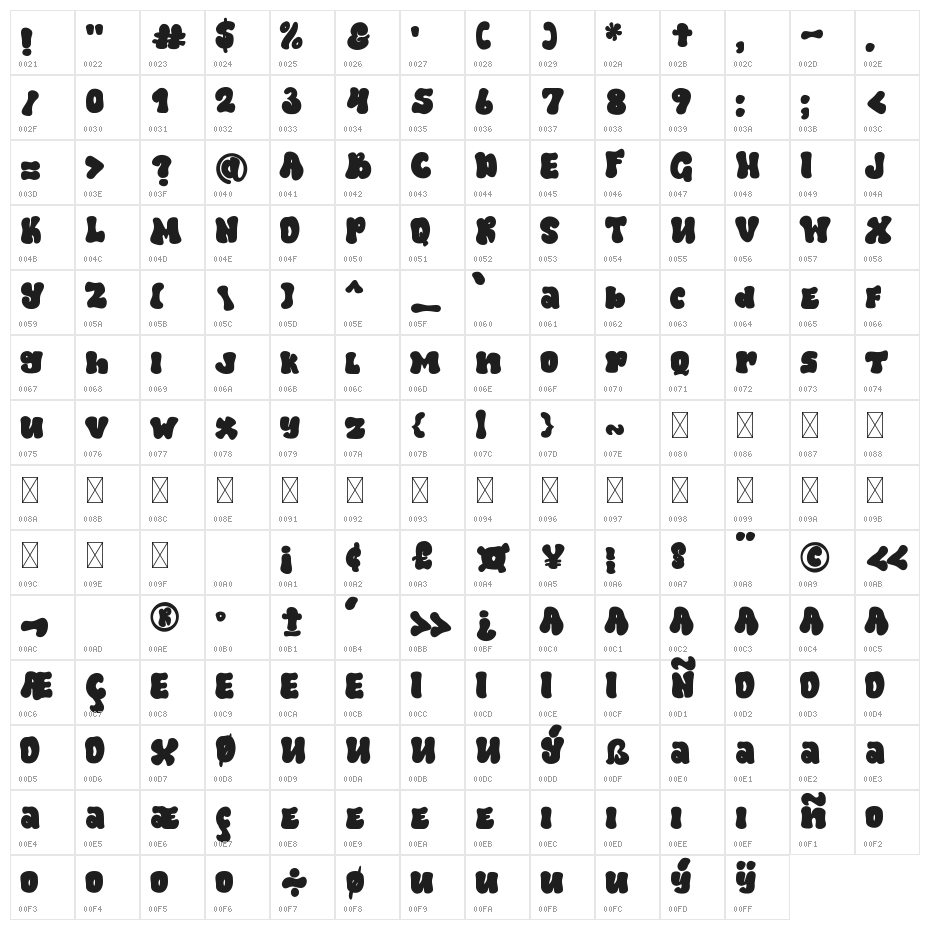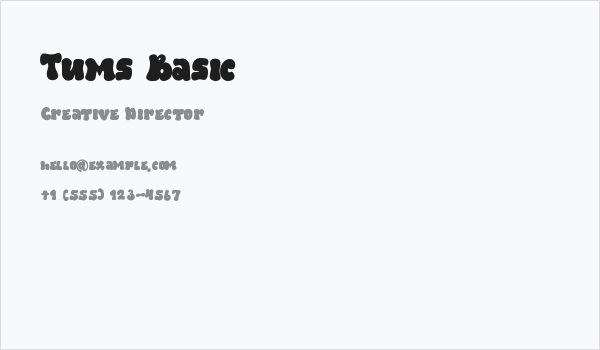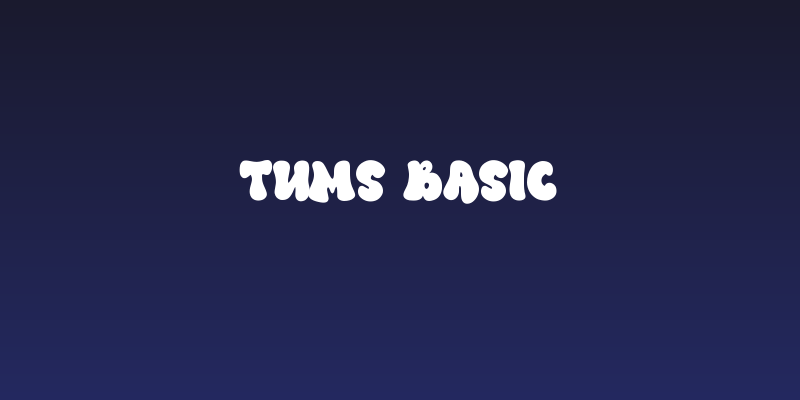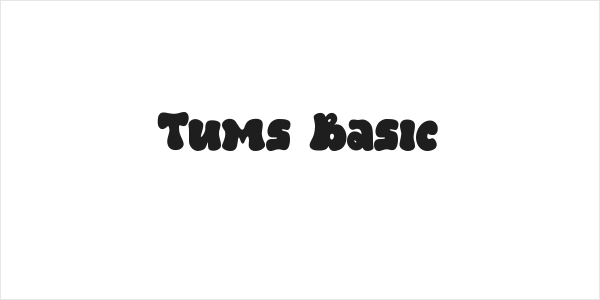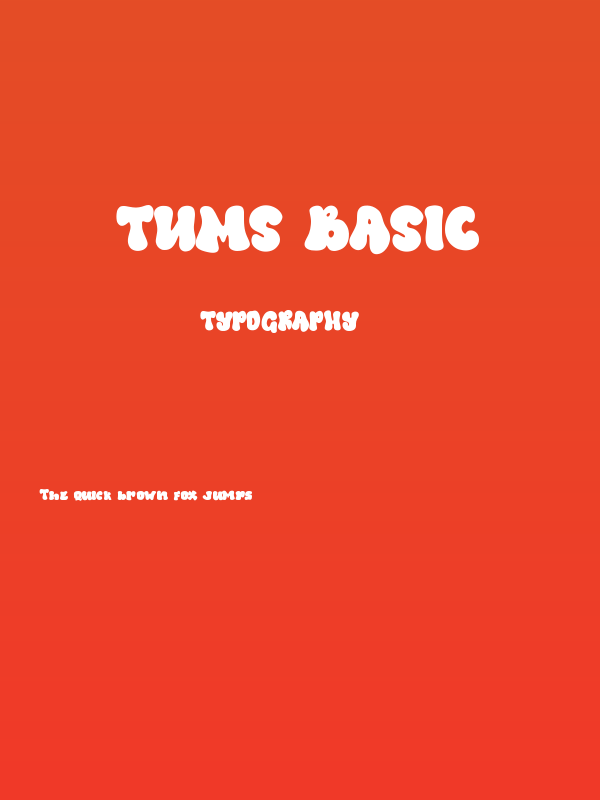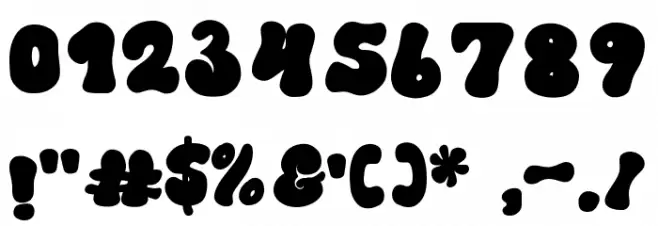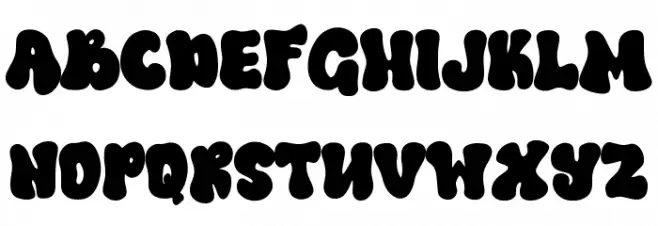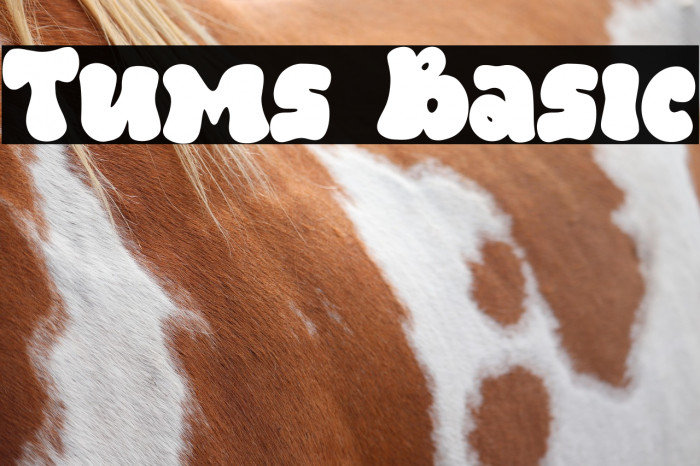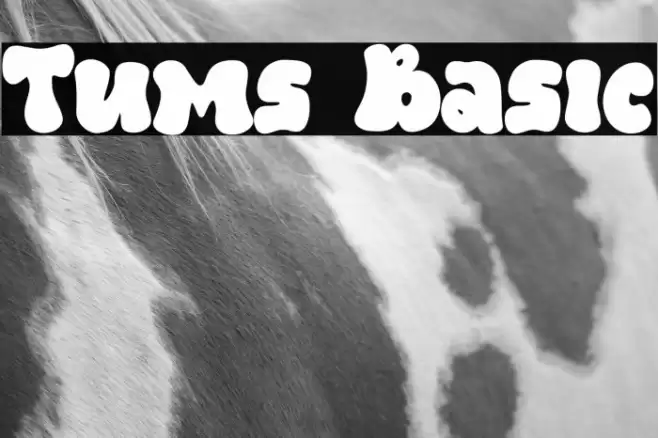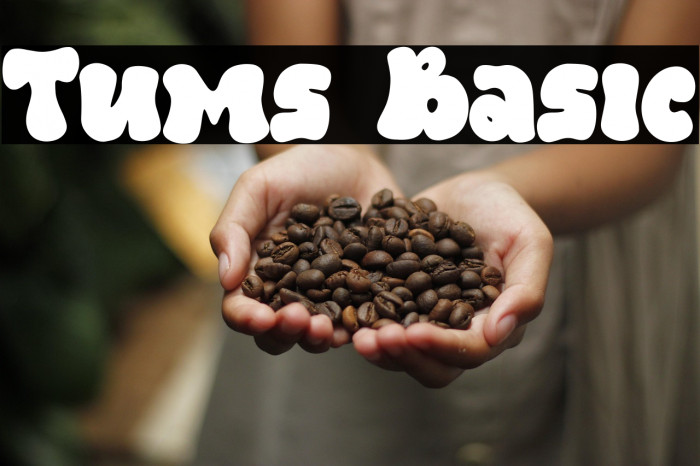
Tums Basic Font
| Style général | Playful, Retro, Modern |
| Projets proposés | Ideal for children's books, party invitations, playful branding, and retro-themed designs. |